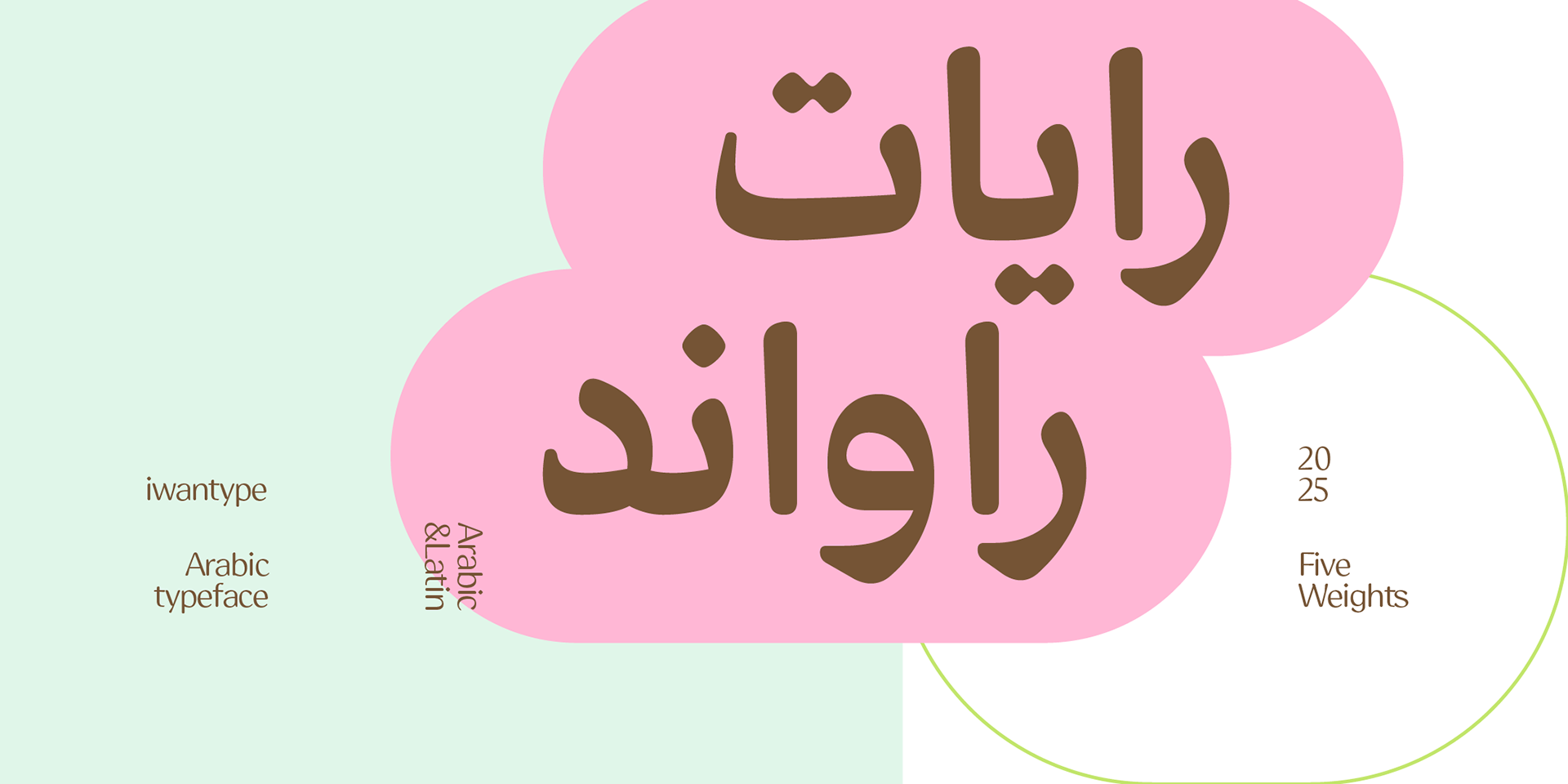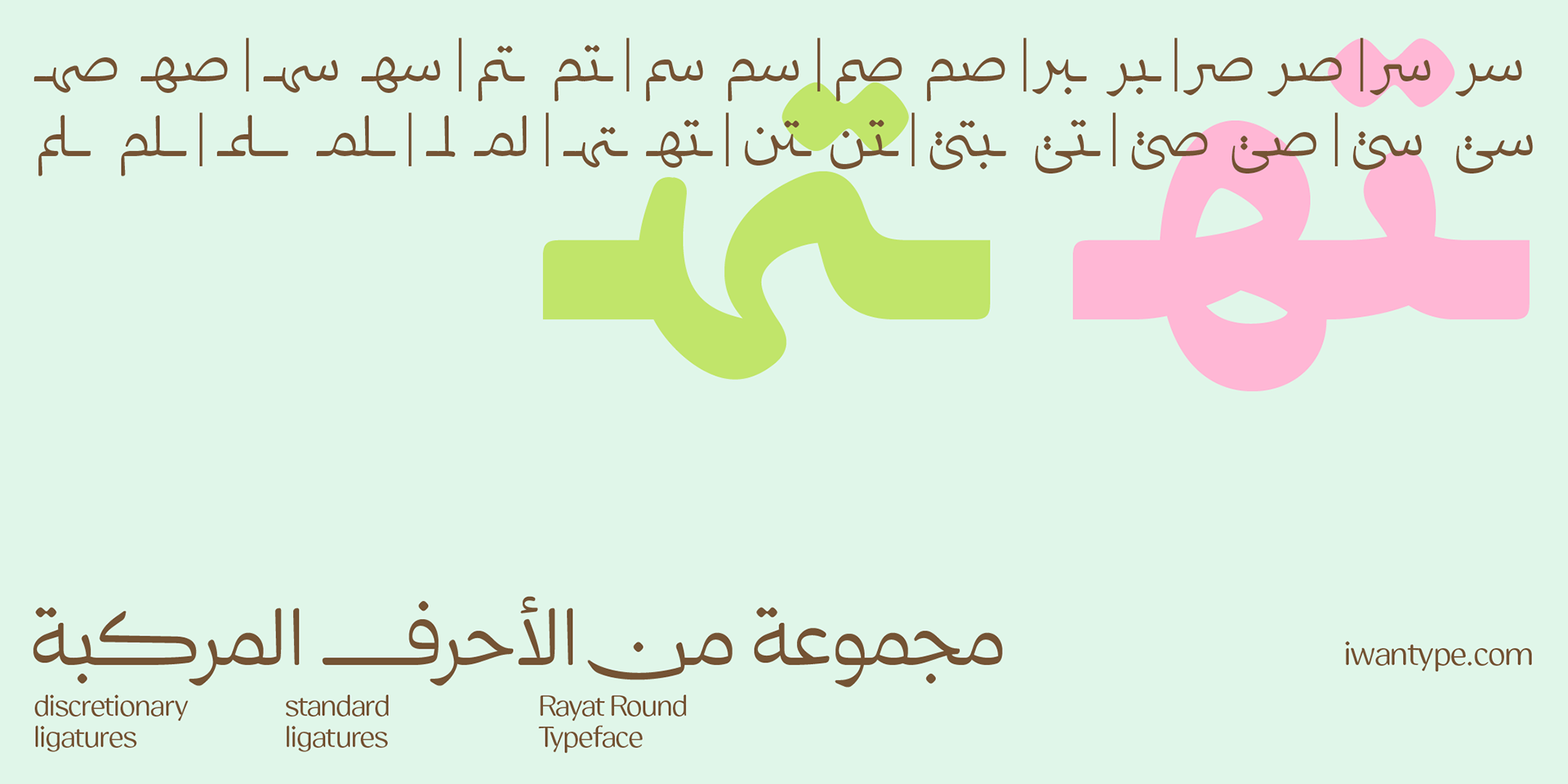
خط رايات راوند - خط نسخ - Rayat round typeface
رايات راوند هو امتداد جديد لعائلة خط رايات، يتميّز بنهايات دائرية ناعمة تضيف طابعًا إنسانيًا ودودًا إلى البنية الهندسية الصارمة للخط الأصلي. حافظ الخط على وضوحه واتزانه، لكنه جاء بنعومة تجعل منه خيارًا مثاليًا للمشاريع المعاصرة التي تستهدف جمهورًا أوسع أو تحمل طابعًا بصريًا مرنًا ومحببًا.